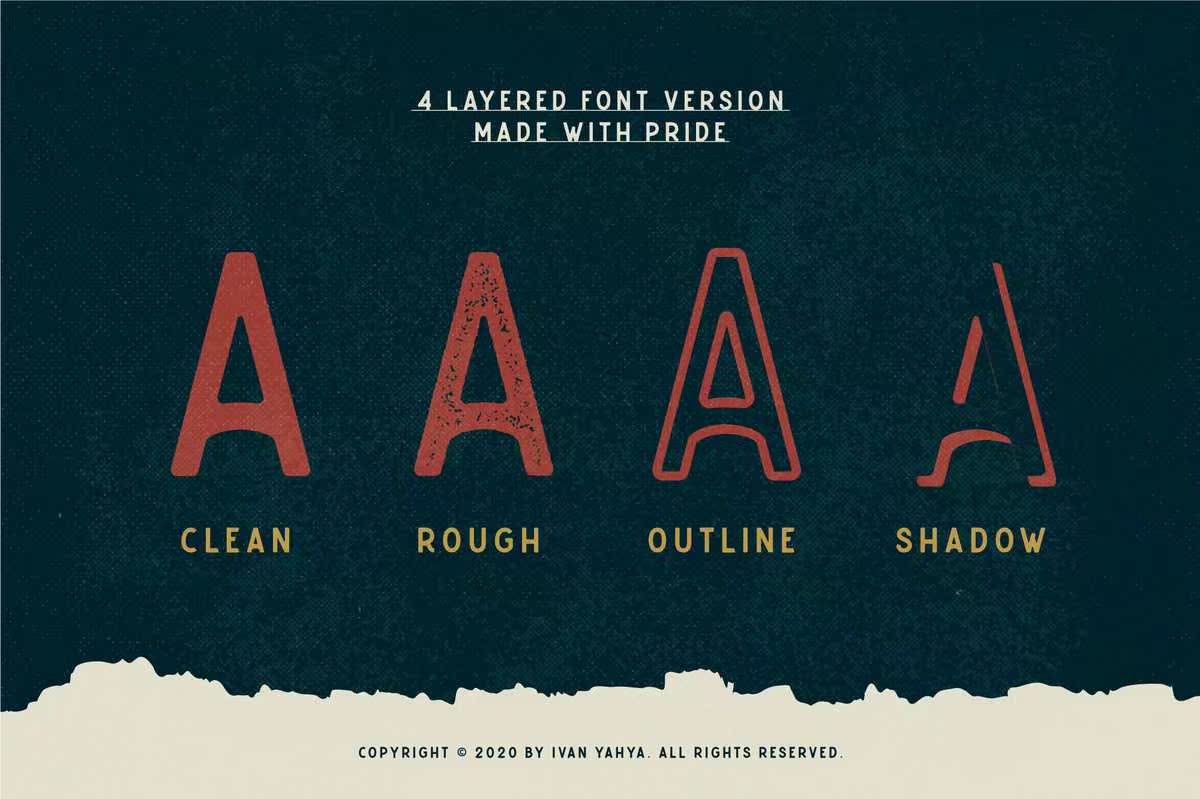
自豪地展示Calton Stype Face。该字体采用简洁简洁的外观设计。使该字体的经典图案更加突出。该字体大约有600个字形字符,包括大写、小写、任意连字和标准连字或其他字符。可用于创作标志性设计,如海报、商品、服装、宣传册、,商务名片和其他。自豪地展示Calton字体。此字体采用简洁简洁的外观设计。使此字体的经典图案更加突出。此字体大约有600个字符,包括大写、小写、任意连字和标准连字以及其他字符。它可用于制作商标海报、商品、,服装、小册子、名片等。